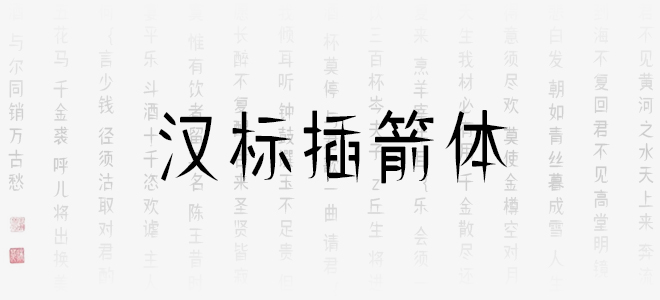
漢標插箭體用了矩形與弧尖兩種圖形元素來構(gòu)建,把這些筆畫概括為飄逸的弧形,并且使左右舒展的筆畫盡量對稱,最大限度地簡化筆畫箭造型。其字形頎長,個性簡靜柔美,宛若身形窈窕、氣質(zhì)不凡的女子,適用于女性時尚類的廣告和產(chǎn)品包裝。歡迎喜歡漢標插箭體的朋友前來下載使用。
漢標插箭體